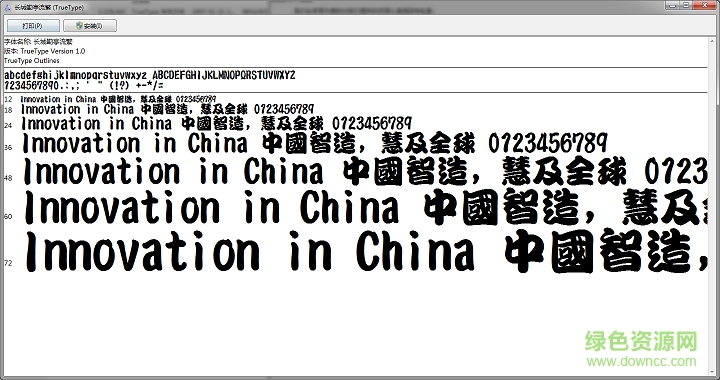
長城勘亭流簡體是一款非常有特色的電腦字體,字形非常的醒目,非常適合用作于標題設(shè)計,有創(chuàng)造需要用到這款字體的朋友可以來綠色資源網(wǎng)免費下載使用!
長城勘亭流簡體是采用日本江戶時代所使用的廣告字體勘亭流體研發(fā)的中文字體,該字體線條粗壯有力,字形端正大方得體,整體效果非常的出色,并且字庫完整,可用于藝術(shù)設(shè)計、包裝印刷、簽名設(shè)計、圖形設(shè)計等領(lǐng)域。